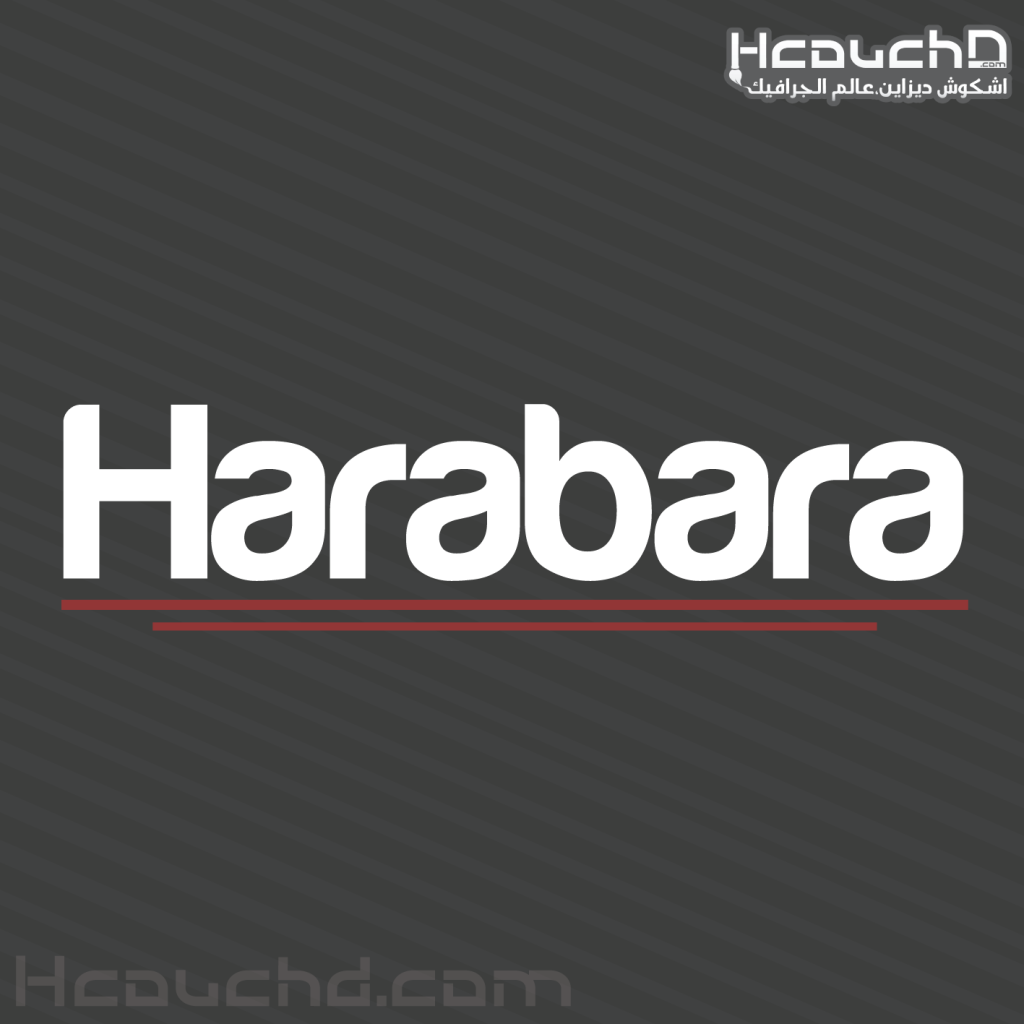
خط Harabara يشبه كتيرا خط مستعمل في لعبة FIFA ، و سبق أن استعملناه في درس ” درس 32 : كيفية تصميم غلاف لعبة بواسطة فوتوشوب + ملف PSD” ، يمكنك تحميل هذا خط من رابط أسفله …